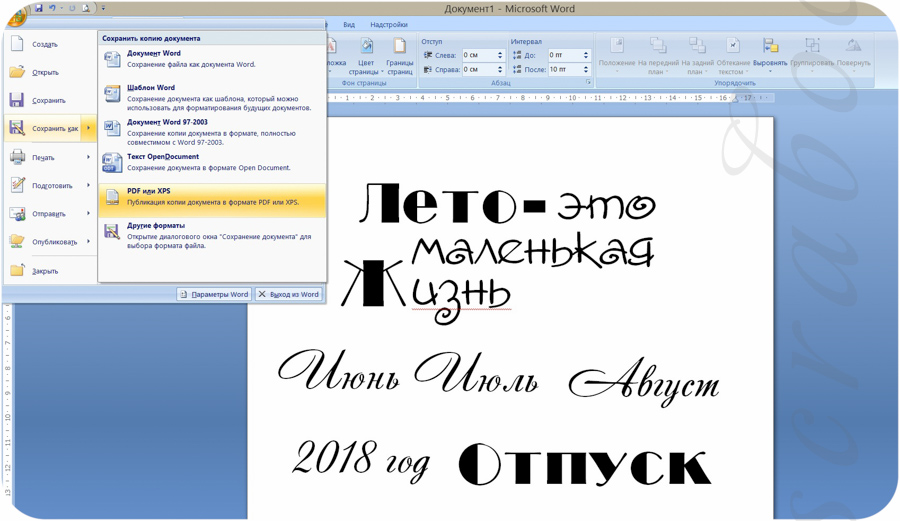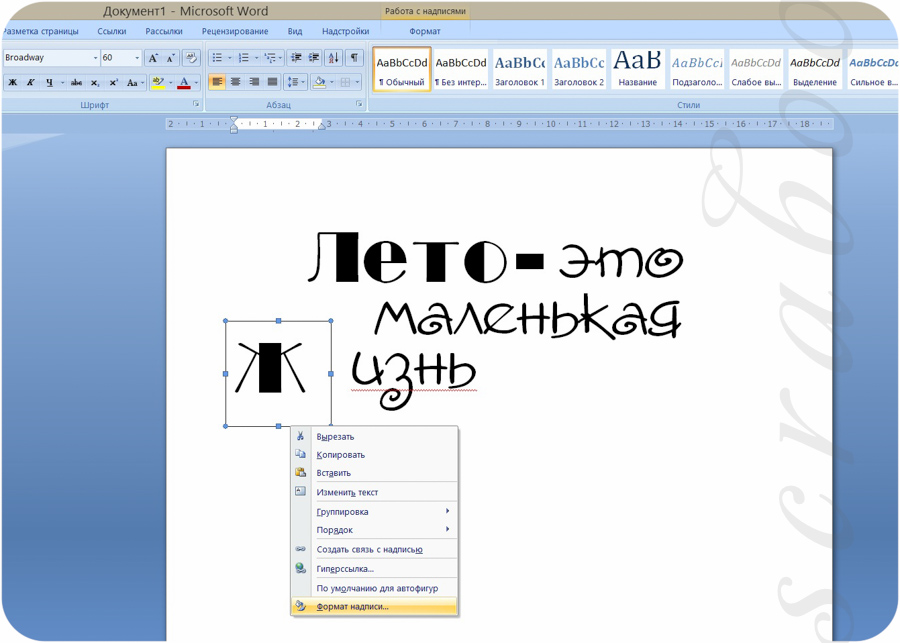
Такой красивый шрифт.
Such a nice font.
Однако есть и такой красивый шрифт, писать которым не составит труда любому человеку.
However, there is such a beautiful font to write which is not difficult to anyone.
У меня нет никаких сомнений, что на данный момент нам нужен очень красивый шрифт.
Because it’s clear to me that what we both need right now is a really good font.
Helvetica существует уже более 50 лет, и он такой же свежий, каким он и был… очевидно, никто и не думал, что он станет таким популярным,
это ведь просто красивый шрифт.
It’s been around for fifty years, coming up, and it’s just as fresh as it was… obviously, it wasn’t intended to be this cool thing,
but it‘s just a beautiful font.
Второй: так ли уж трудно самому сделать свою страничку в интернете,
презентацию в Power Point на русском и английском языках или хотя бы просто подобрать красивый шрифт для логотипа своего проекта?
Second: Is it really difficult to make Power Point presentation
in English and Russian languages, or even just pick a nice font for the logo of your project?
Я осознал гениальность этого проекта, а поскольку гарнитура может просто затеряться среди прочих довольно обычных шрифтов на Linotype.
com, я написал рецензию, чтобы сказать:
может, это и не самый красивый шрифт на свете, но он стоит того, чтобы на него взглянуть.
I realized the ingenuity of his project, and since the typeface may simply be lost among all the other very normal typefaces on the Linotype. com,
I wrote the review to say,»This may not be the most beautiful typeface ever, but it might be something worth looking at.
Красивые шрифты, Красивое настроение!
Beautiful fonts, Beautiful mood!
Очень понравился смелый яркий дизайн и красивые шрифты.
I love this bright bold design and it‘s beautiful fonts.
Подберите красивый фон, выберите нужный шрифт, выставьте необходимое положение и добавьте потрясающие эффекты.
Select beautiful background, choose the needed font, take apropriate position and add stunning effects.
Бывает шрифт красив, как растение, он слишком тонок, а может
быть наоборот- слишком плотным.
Sometimes a script is so beautiful that it looks like a herb and it is very thin,
and sometimes it can be dense.
В какой-то момент ко всем нам, глупеньким дизайнерам, приходит понимание, что одно дело- красивые буквы, каждая по отдельности, а другое дело, когда весь шрифт целиком у тебя работает- и читается, и стилистически как надо и т. д.
At some point all of us simple designers realise that beautiful letters, taken individually, are one thing, while it’s quite another thing altogether when the whole font is working for you-
and is legible, with the style just as you need it to be and so on.
Это может быть оригинальный красивый рисунок, орнамент, памятная надпись,
выполненная красивым прописным шрифтом и т. д.
This may be the original beautiful pattern, ornament, commemorative inscription made beautiful uppercase letters, etc.
Если вглядеться в рисованный шрифт книги, то легко можно убедиться, что он строен, ажурно красив, отточенно артистичен во всех своих нюансах,
что он гармонично сочетается с иллюстрациями и оформительскими элементами, как легок он для восприятия читателя- зрителя даже в миниатюрном варианте издания.
The book typography is plain, exquisitely beautiful, perfectly artistic in all its nuances; it harmoniously fits
the illustrations and decorative elements, it is easy for the readers even in a miniature edition.
Большая подборка красивых и качественных шрифтов.
Large collection of beautiful and high-quality fonts.
Лазерная гравировка позволяет нанести на металлическую поверхность ручки любое изображение, в том числе, самые сложные надписи,
выполненные красивыми старинными шрифтами.
Laser engraving allows you to put on a metal surface of the handle any image, including the most complex labels,
made beautiful old fonts.
Эта коллекция шрифтов включает в себя 50 красивых рукописных шрифтов для выражения любого настроения.
Сохраняйте одинаковые шрифты во всем резюме, чтобы оно выглядело единым и аккуратным.
Шрифты, которые лучше не использовать в резюме
Теперь, когда мы рассмотрели лучшие шрифты для вашего резюме, стоит упомянуть шрифты, которые никогда не следует использовать в резюме.
Надеюсь, из примеров понятно почему…
Воздействие
Некоторые кандидаты используют Воздействие в попытке оказать влияние на читателей, но это не оказывает положительного влияния.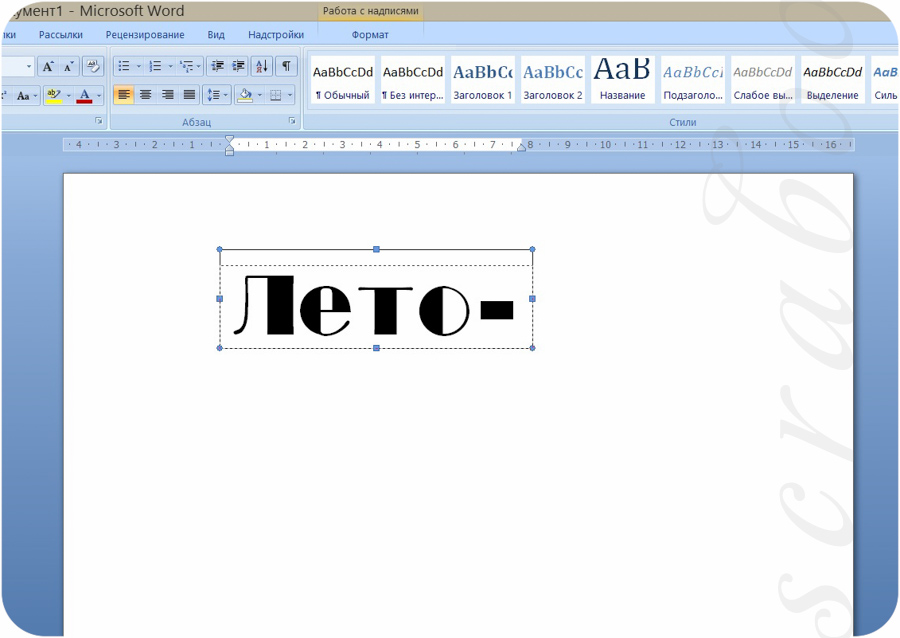